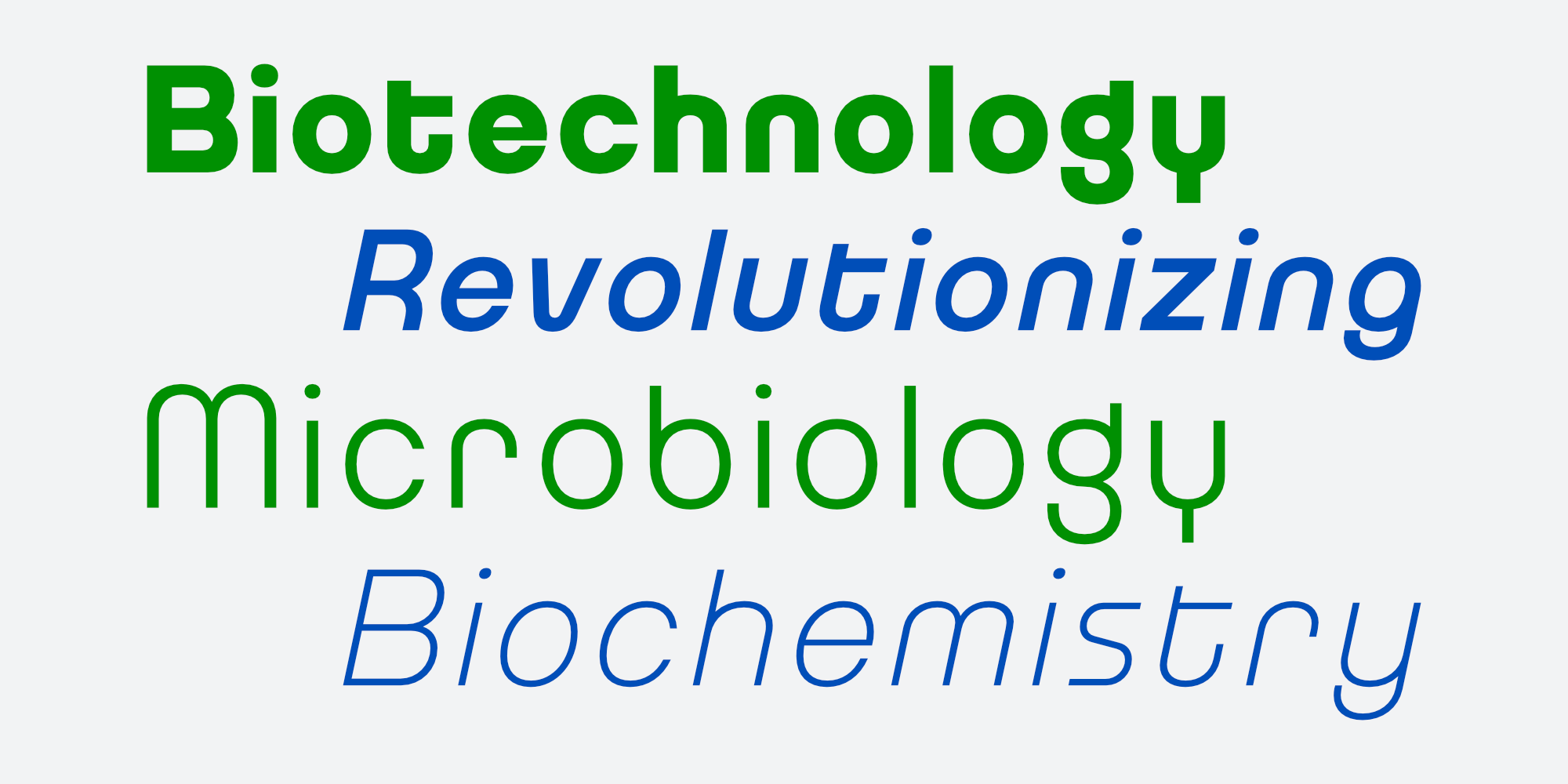
ชีวะเท็กซ์ | Chewatext
ชื่อฟอนต์ : ชีวะเท็กซ์ | Chewatext
Chewatext เป็นแบบอักษรซานเซอริฟที่มีรูปลักษณ์เรียบง่าย เรขาคณิต และเทคโนโลยี มีให้เลือกใช้ถึง 18 สไตล์ รองรับตัวอักษรลาติน 1 และอักษรไทย ทำให้เป็นตัวเลือกที่ดีที่สุดสำหรับโปรเจ็คร่วมสมัย ไม่ว่าจะเป็นงานสิ่งพิมพ์ต่าง ๆ ทั้งออนไลน์และออฟไลน์
Chewatext is a sans serif typeface that minimalism, geometric, and technological look. This versatile font family offers a staggering 18 styles, support Latin-1 and Thai Unicode for character. Making it the ultimate choice for contemporary design projects. Whether it is various printed works, both online and offline.